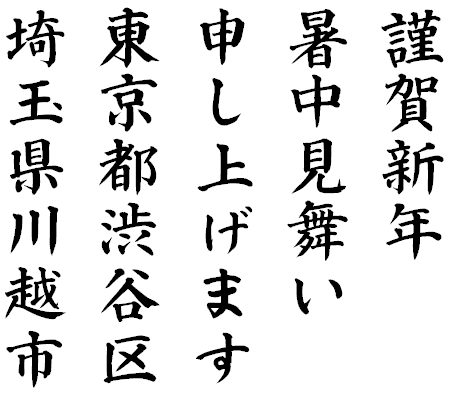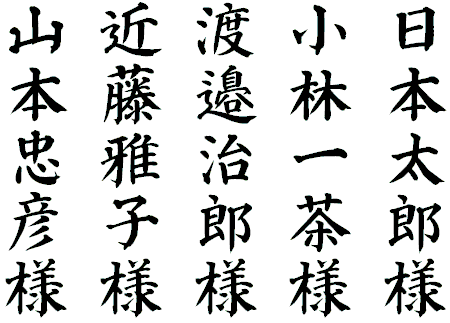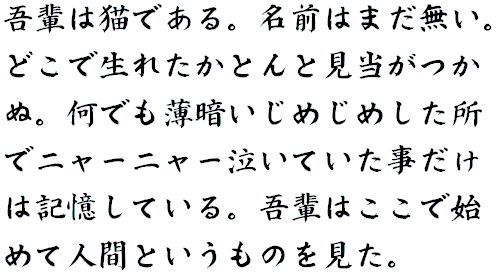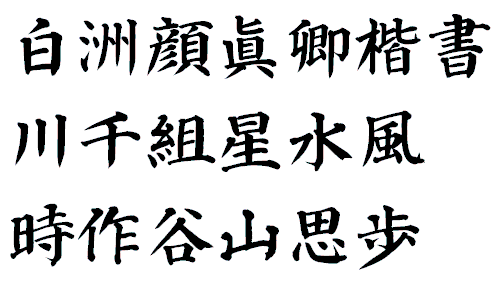
NM白洲顔眞卿楷書
- 書家の中本白洲先生が字母を書かれた毛筆フォントです。
- 中国の書道家、顔眞卿(がんしんけい、709〜785年)の書風で作成しました。
- 株式会社日本書技研究所との共同開発です。
- 書家が用紙に書かれた文字をそのままフォントにしており、画一的にしないで手書きの味を出しているため文字が統一されていない場合があります。